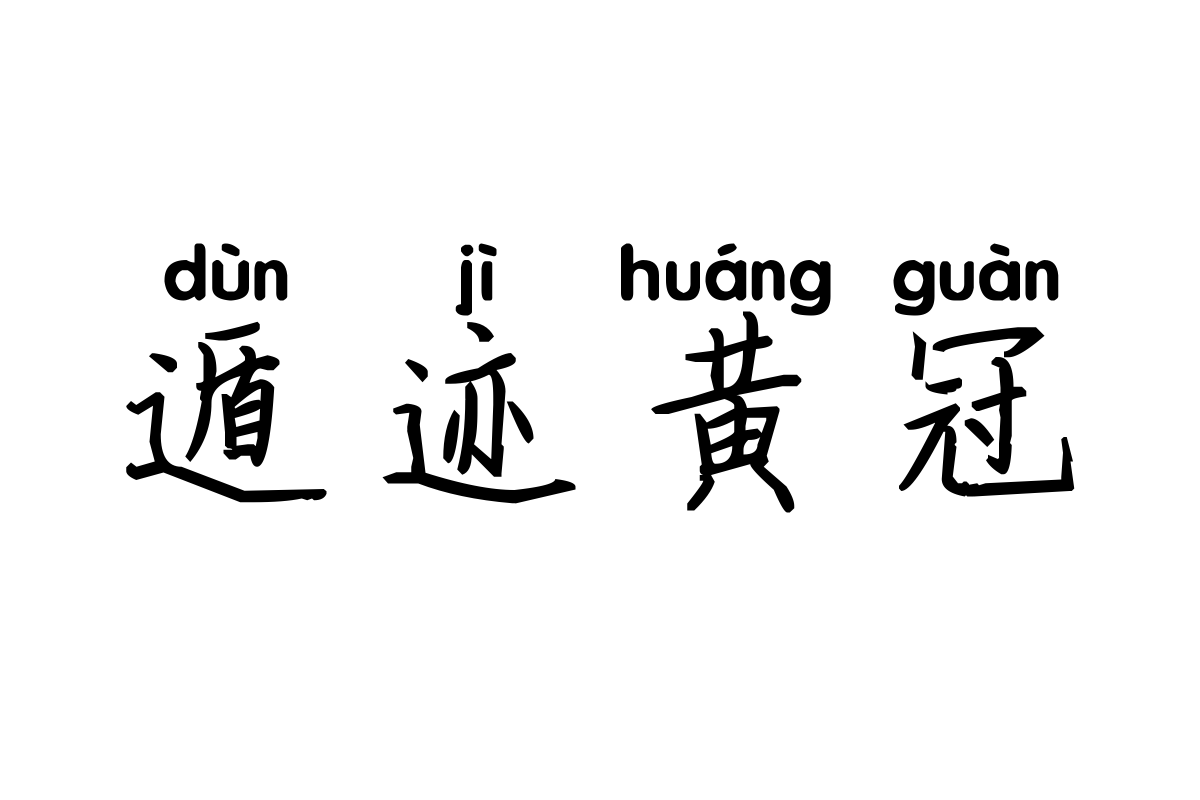
米开不负时光拼音体是一种中文字体,由设计师米开设计。这种字体的特点是笔画流畅,字形优美,适合用于书写和排版。
字体特点:
1. 笔画流畅:米开不负时光拼音体的笔画线条流畅自然,给人一种优雅的感觉。
2. 字形优美:这种字体的字形设计精美,线条粗细适中,给人一种舒适的感觉。
3. 适合书写:由于笔画流畅,这种字体非常适合用于书写,可以让人轻松地完成文字输入。
4. 适合排版:这种字体的字形设计精美,线条粗细适中,适合用于排版,可以提升整体的视觉效果。
总之,米开不负时光拼音体是一款非常实用的中文字体,无论是用于书写还是排版,都能给人带来良好的视觉体验。